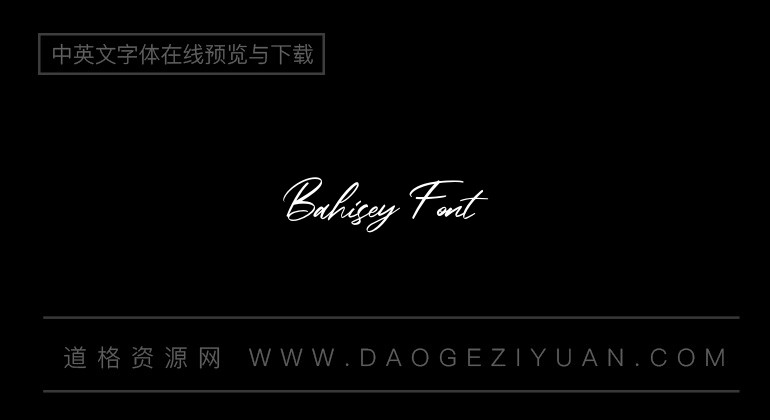
Bahisey Font
Bahisey Font是一种免费的手写风格字体,由设计师Ahmet Altun于2017年创建。字体包含所有基本字符,包括大写字母、小写字母、数字和标点符号,适用于各种设计项目,如海报、名片、宣传册和网站设计等。 Bahisey Font的风格非常独特,其字母形状像是手写,但又具有一定的均衡和规则性,使其非常适合用于体现个性和创意的设计。此外,该字体还包含了一些额外的装饰性字符,如花朵和星星,可用于美化设计作品。 总之,Bahisey Font是一款非常有趣和实用的字体,可以为您的设计项目带来一份独特的风格。
Bahisey Font是一款非常不错的手写艺术字体,具有很好的视觉感,适合于文化类的宣传设计、商业类品牌的广告和产品包装设计以及个性化文字排版等较多场景。